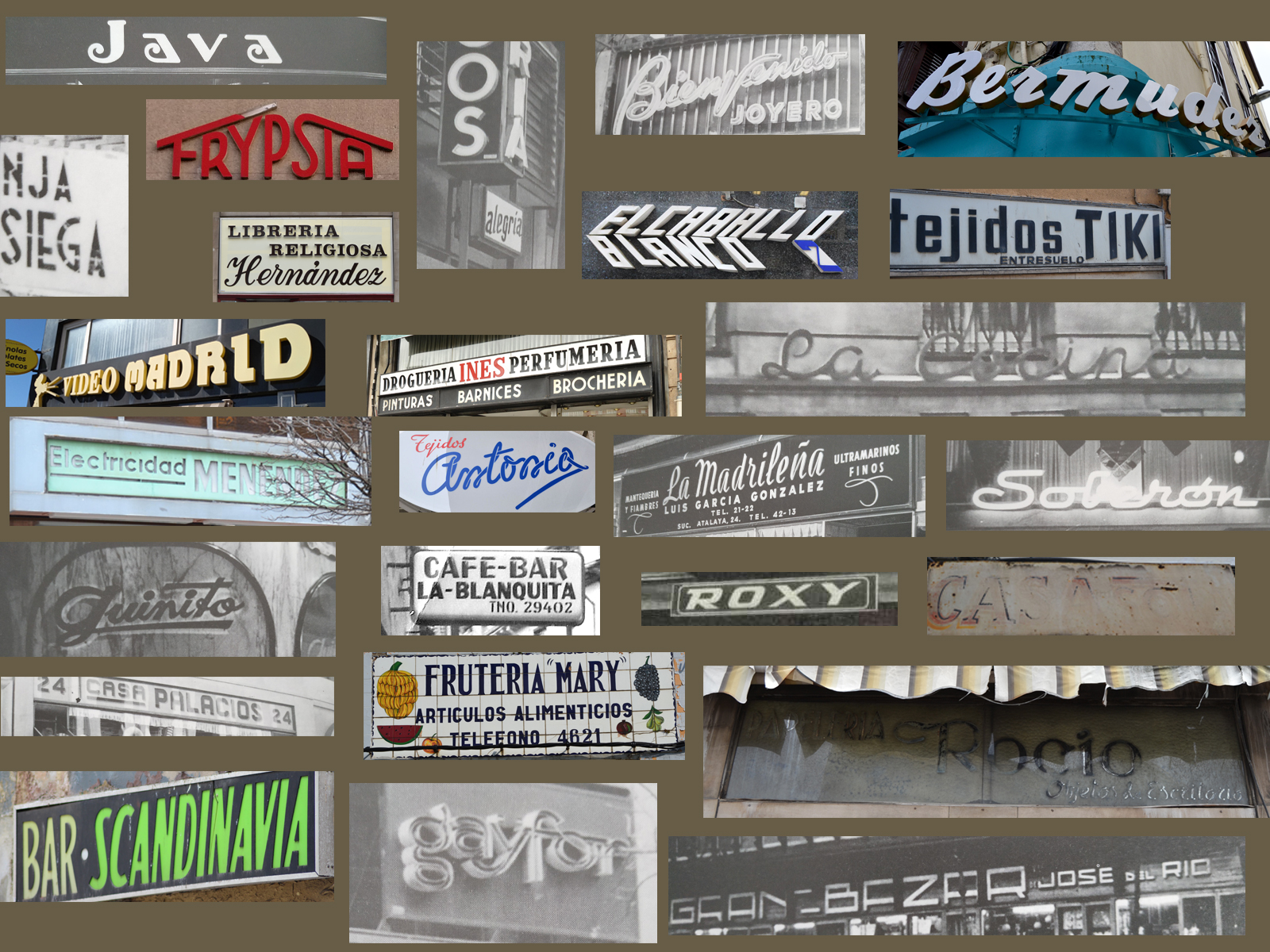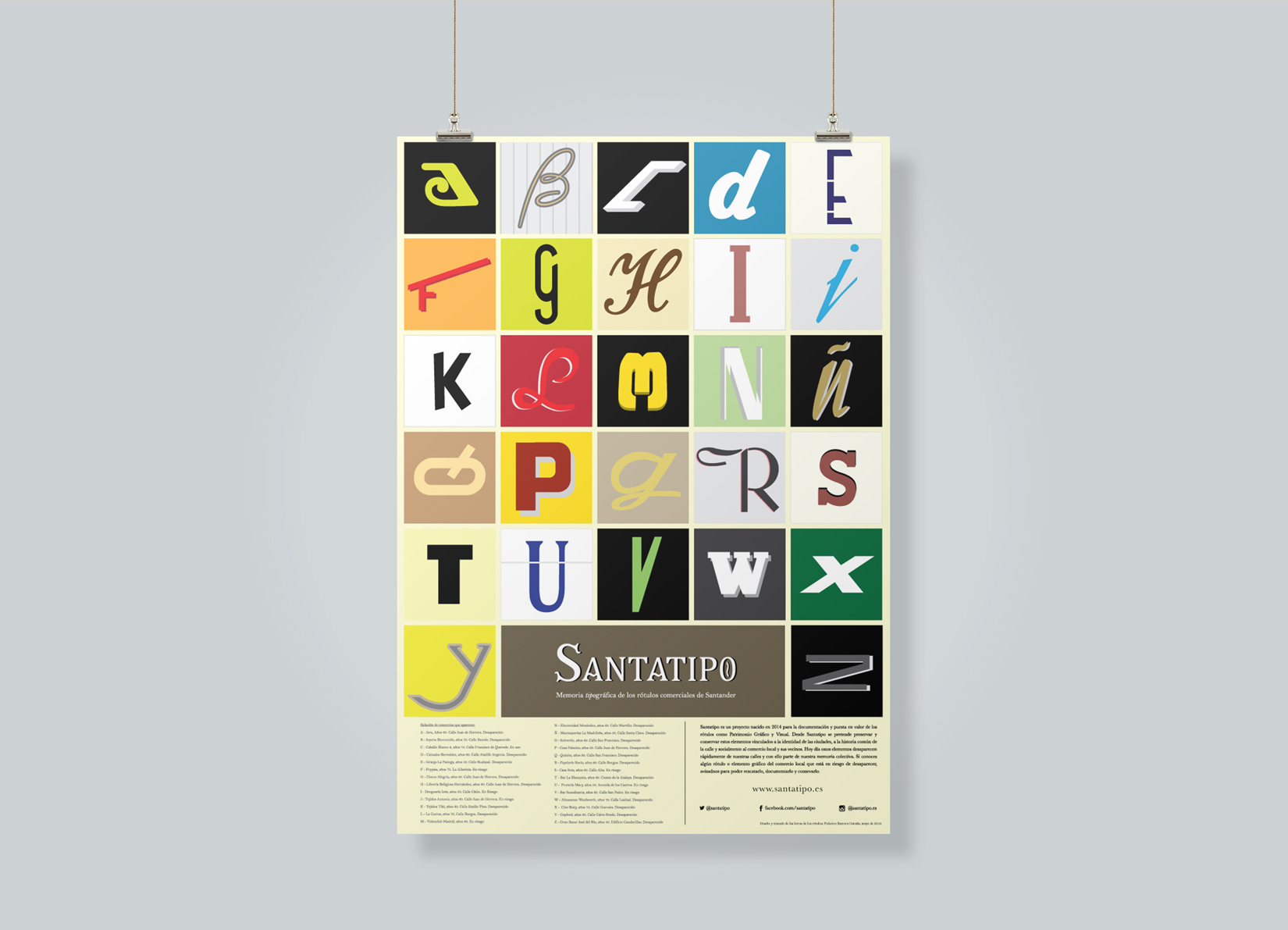
Poster Abecedario Ed. Crowdfunding
Este es el poster se basa en la versión que algunos mecenas se llevaron como recompensa por el apoyo en la campaña de crowdfounding del libro «Santatipo: Memoria tipográfica de los rótulos comerciales de Santander». En formato A3, este mosaico de formas y colores recoge veinticuatro letras que han formado parte del paisaje gráfico de Santander. La gran mayoría ya han desaparecido y otras están en riesgo de hacerlo si no lo salvamos.
Esto son los comercios santanderinos que forman parte del poster:
A – Java, Años 60. Calle Juan de Herrera. Desaparecido
B – Joyería Bienvenido, años 70. Calle Becedo. Desaparecido
C – Caballo Blanco 2, años 70. Calle Francisco de Quevedo. En uso
D – Calzados Bermúdez, años 60. Calle Ataúlfo Argenta. Desaparecido
E – Granja La Pasiega, años 50. Calle Rualasal. Desaparecido
F – Frypsia, años 70. La Albericia. En riesgo
G – Discos Alegría, años 60. Calle Juan de Herrera. Desaparecido
H – Librería Religiosa Hernández, años 80. Calle Juan de Herrera. Desaparecido
I – Droguería Inés, años 50. Calle Cádiz. En Riesgo
J – Tejidos Antonio, años 80. Calle Juan de Herrera. En riesgo
K – Tejidos Tiki, años 80. Calle Emilio Pino. Desaparecido
L – La Cocina, años 70. Calle Burgos. Desaparecido
M – Videoclub Madrid, años 80. En riesgo
N – Electricidad Menéndez, años 60. Calle Martillo. Desaparecido
Ñ – Mantequerías La Madrileña, años 50. Calle Santa Clara. Desaparecido
O- Soberón, años 60 .Calle San Francisco. Desaparecido
P – Casa Palacios, años 50. Calle Juan de Herrera. Desaparecido
Q – Quinito, años 90. Calle San Francisco. Desaparecido
R – Papelería Rocío, años 60. Calle Burgos. Desaparecido
S – Casa Sota, años 60. Calle Alta. En riesgo
T – Bar La Blanquita, años 60. Cuesta de la Atalaya. Desaparecido
U –  Frutería Mary, años 50. Avenida de los Castros. En riesgo
V – Bar Scandinavia, años 80. Calle San Pedro. Rescatado
W – Almacenes Woolworth, años 70. Calle Lealtad. Desaparecido
X –  Cine Roxy, años 70. Calle Guevara. Desaparecido
Y – Gayford, años 90. Calle Calvo Sotelo. Desaparecido
Z – Gran Bazar José del Río, años 50. Edificio Gandarillas . Desaparecido